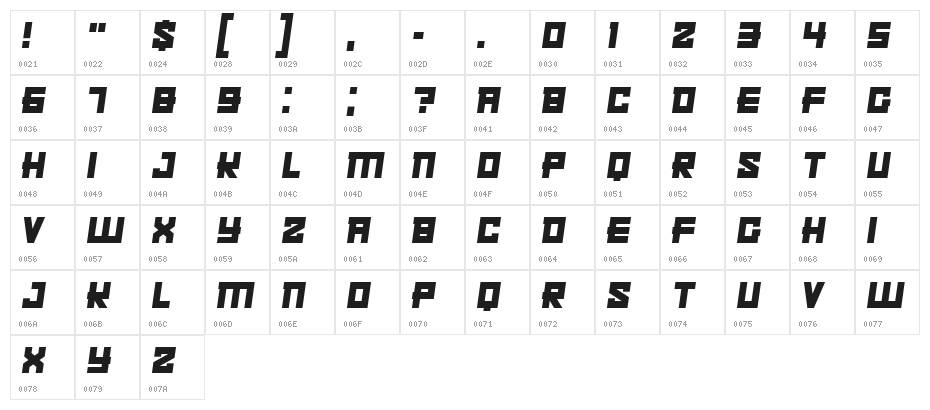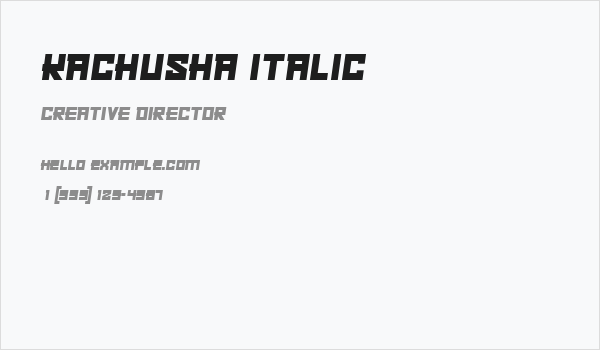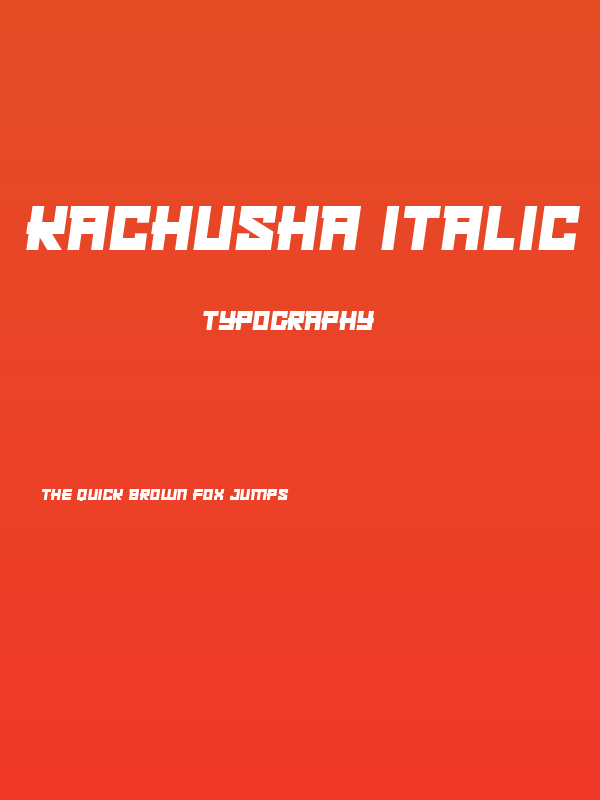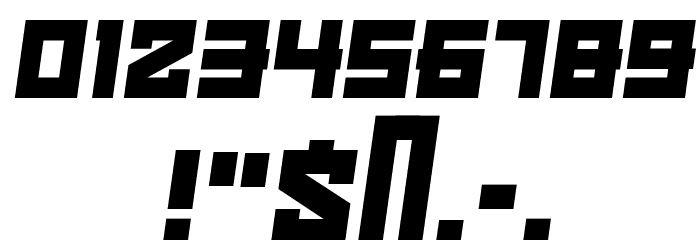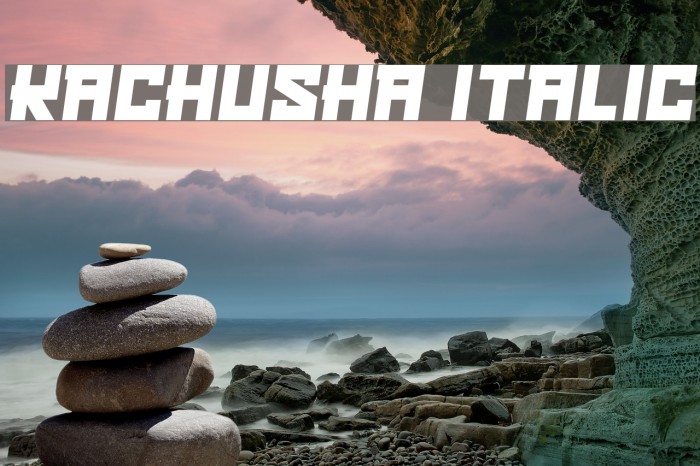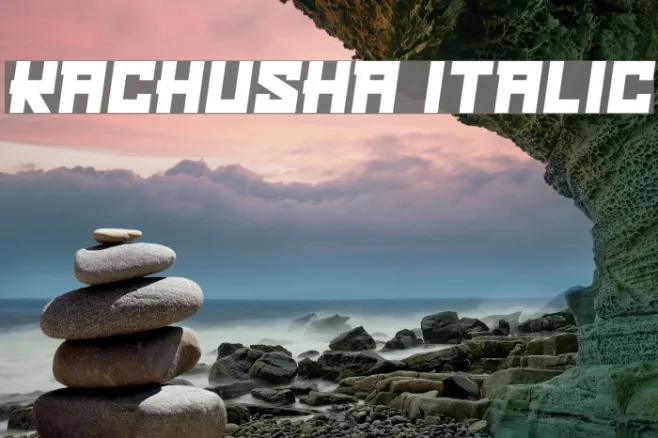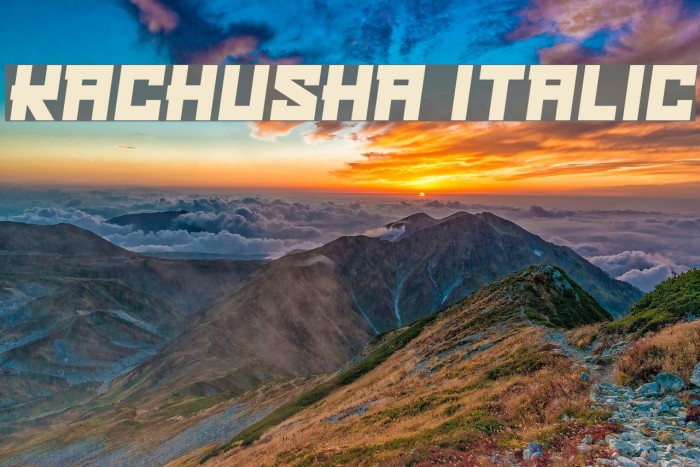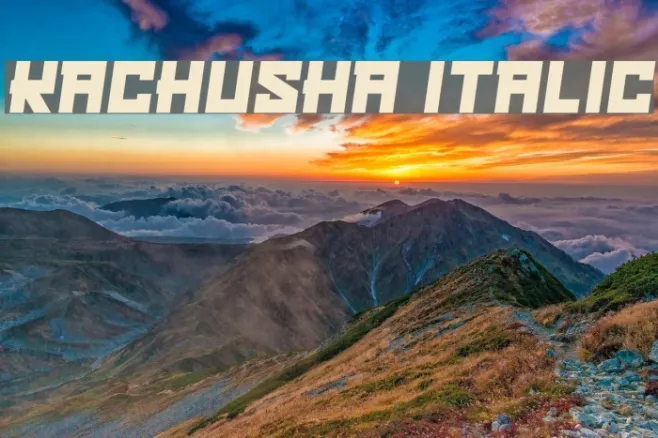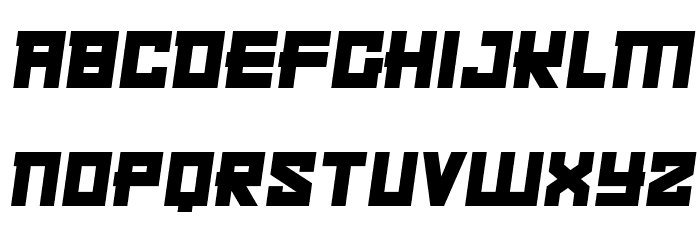
Kachusha Italic Font
| Caso de uso | Logos, Headlines, Posters |
| Proyectos propuestos | Ideal for branding, sports team logos, video game titles, and poster designs that require a modern and impactful look. |